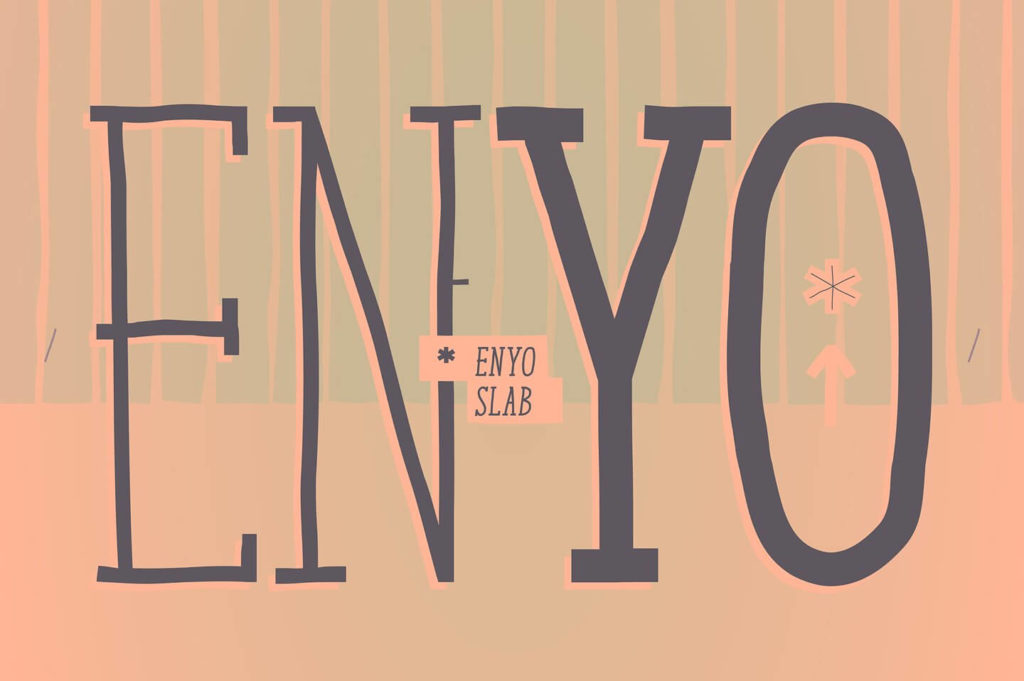
Шрифт Enyo Slab
Шрифт Enyo Slab — это декоративный брусковый шрифт с эффектом рукописного письма от словолитни Antipixel. Гарнитура была разработана дизайнером Julia Martinez Diana и выпущена в 2014 году . Сочетает в себе неформальный, «живой» рисунок с характерными брусковыми засечками, что придаёт тексту одновременно дружелюбный и основательный вид . Отлично подходит для акцентного использования в заголовках и коротких текстах. Шрифт поддерживает кириллицу и латиницу, а также греческий алфавит, что делает его отличным выбором для проектов на русском языке, где нужен нестандартный, запоминающийся стиль . Если вы ищете необычный шрифт с рукописным характером, вы можете скачать его для ознакомления прямо с этой страницы.